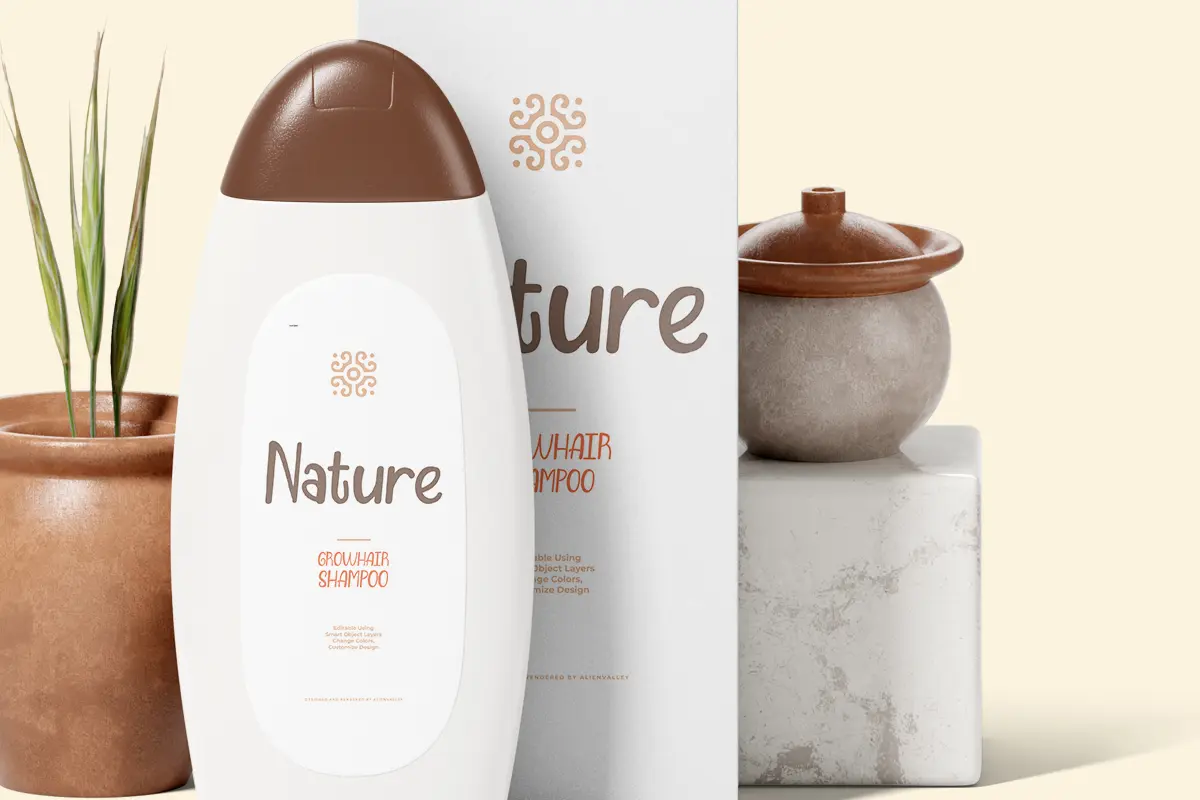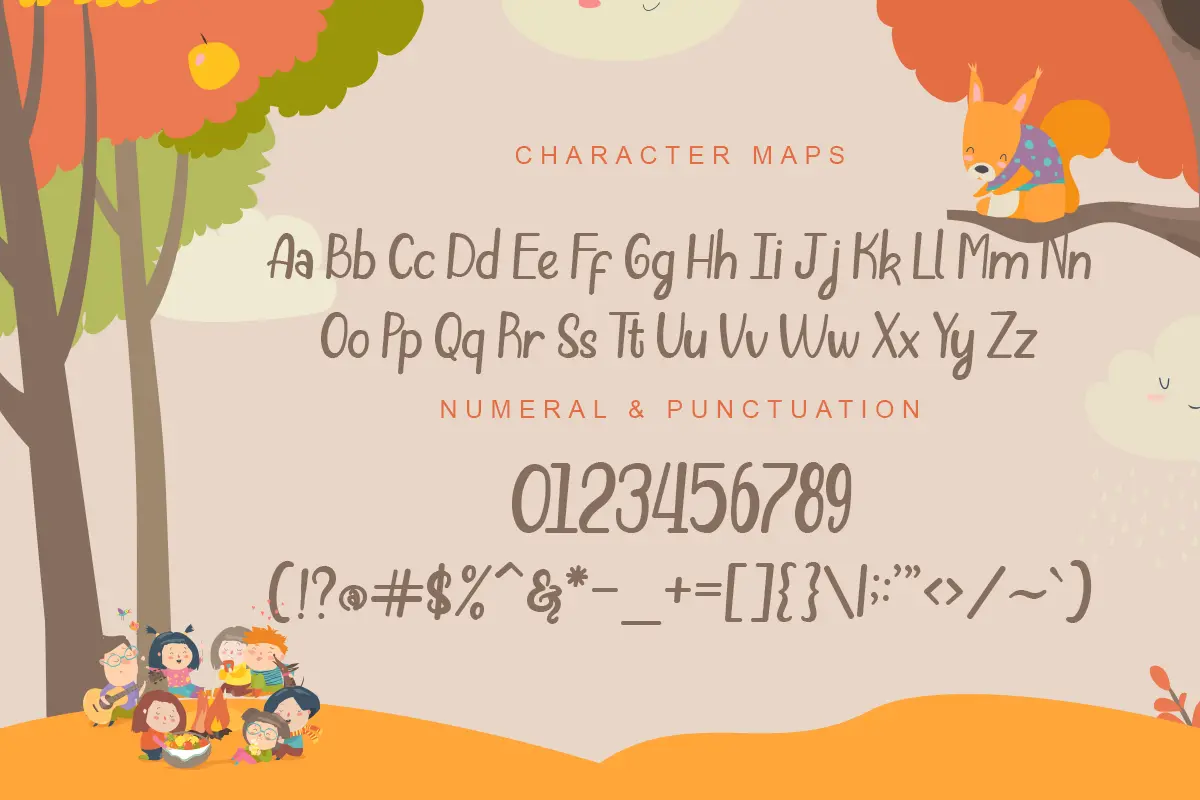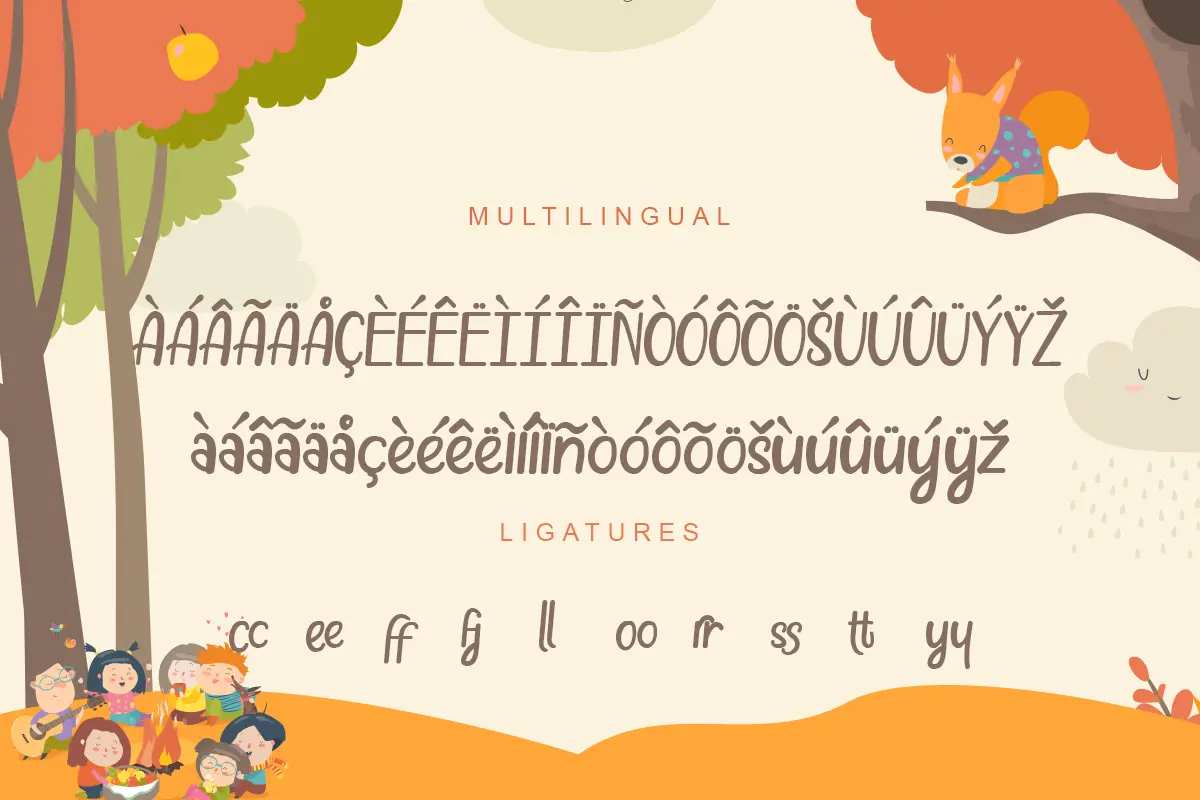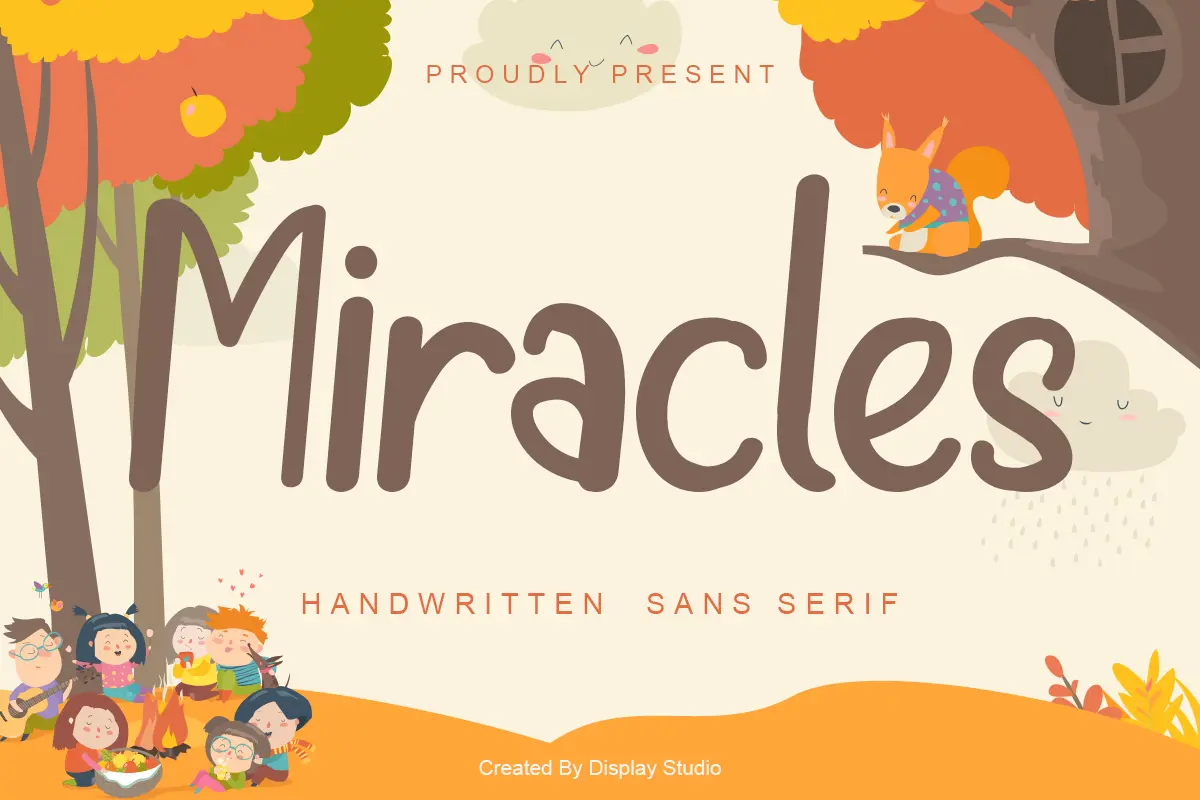
فونت کودکانه و بامزه رایگان
فونت Miracles یک فونت کودکانه زیبا، مرتب و دوستانه است که با ظاهری ساده و در عین حال جذاب طراحی شده. این فونت برای کسانی ساخته شده که به دنبال ظاهری تازه، دلنشین و خوانا در طراحیهای خود هستند.
⭐ ویژگیهای محصول:
- سبک: Handwritten Font – فونت دستنویس دوستانه و خوانا
- طراحی: تمیز، مرتب و ساده با حس صمیمی
- انتخابی عالی برای طراحیهای مدرن و خلاقانه
🎯 موارد استفاده:
- طراحی لوگوهای ساده و دوستانه
- کارتهای تبریک و دعوتنامههای شیک
- پوسترها و بنرهای تبلیغاتی با حس تازه و دلنشین
- بستهبندی محصولات سبک و مینیمال
- پروژههای دیجیتال و وبسایتهای خلاقانه